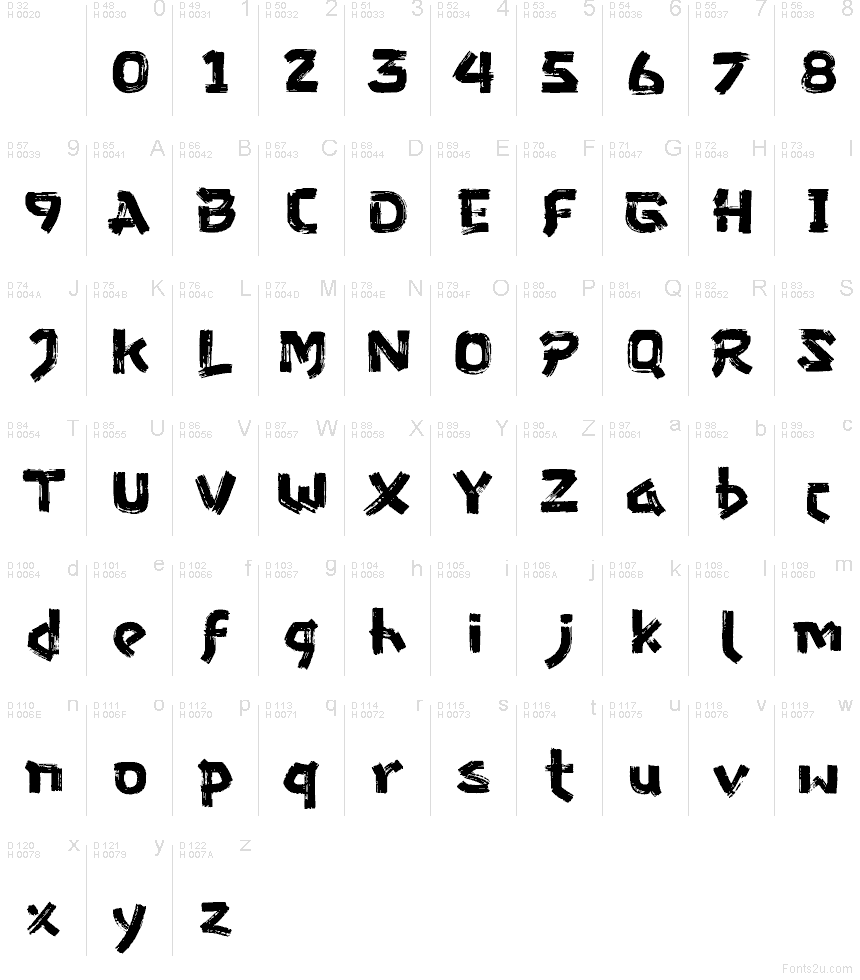
Gozaru od tkzgraphic je bezplatné štětcové písmo s nádechem syrovosti a ruční práce. Písmena vypadají, jako by byla vytažena pořádně namočeným štětcem – s roztřepenými okraji, útržkovitými tahy a robustními tvary. Je to něco mezi graffiti tagem a plakátovým písmem, které díky své ostrosti udrží vizuální sílu i v logotypech.
Hodí se pro hudební vizuály, streetwear, herní tituly, plakáty na akce i výrazné nadpisy na sociálních sítích, kde záleží více na dynamice než na uhlazenosti. Použijte ho v krátkých titulcích, na obálkách nebo jako velký úvodní nápis, když chcete, aby ta „škrábaná“ textura mluvila za vás.